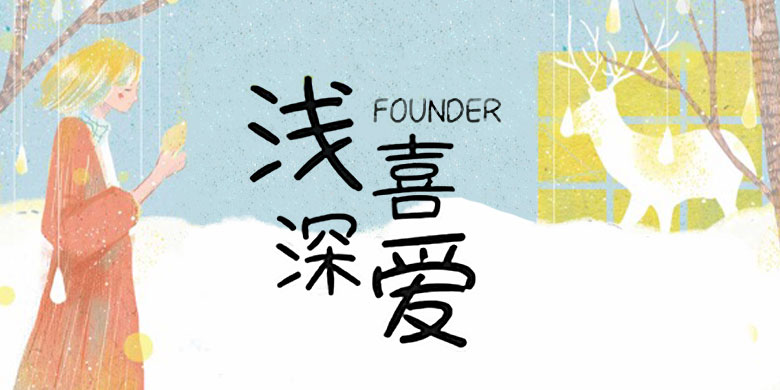
字体介绍 品牌:方正手迹设计师:俞亦婷发行时间:2019字库编码:大陆简体(GB2312-80)分类:创意书写字体属性:精品字 英文名称:FZSJ-QIANXSA.TTF 浅爱深喜这款字体线条简洁干净,字形偏扁,重心平稳,规整中带着少女的温文尔雅,文艺感十足。适用于少年儿童类、文艺类的书刊、漫画综艺字幕、品牌广告和产品包装设计,以及社交网络的个性化用字。 字体下载 官方下载